가독성 좋은 폰트의 종류
한글 폰트는 이전의 제한적이었던 고딕체, 명조체만이 아니라 지역을 대표하고 기업을 대표하는 다양한 디자인의 폰트들이 많이 개발되어 우리 생활 속에 다양하게 활용되고 있습니다. 이처럼 다양한 폰트들을 가독성 좋은 폰트로 디자인에 어떻게 사용하는 것이 좋은지 설명드리겠습니다. 우리가 가장 많이 사용하는 한글 폰트는 세 가지가 있는데요 바로 고딕체, 명조체, 필기체입니다.
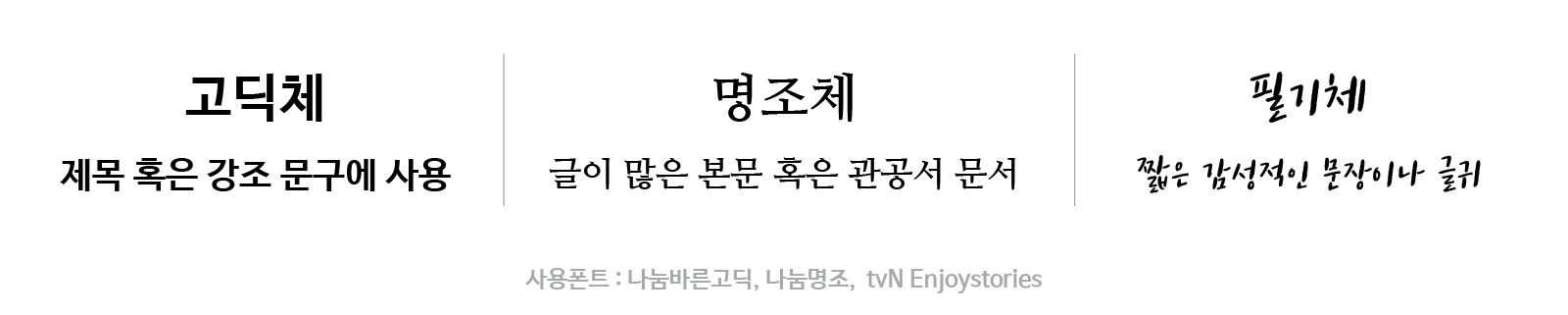
고딕체는 주로 제목이나 강조하고 싶은 단어나 문장에 사용합니다. 명조체는 주로 글의 내용이 많은 본문이나 관공서의 문서에 사용합니다. 필기체는 감성적인 광고지나 짧은 글에 자주 사용합니다. 이처럼 한글 폰트는 글자의 모양과 그에 따른 사용 목적이 분명하며 이것을 잘 지켜서 디자인을 하였을 때 보기 편하고 잘 정리된 느낌을 전달합니다. 이것을 우리는 가독성이 좋은 디자인이라고 말합니다. 가독성이 좋은 한글 폰트 디자인을 하기 위해서 실무에서 자주 사용하는 몇 가지 규칙을 소개해 드리겠습니다. 이 폰트 규칙은 고딕체와 명조체를 사용할 때 주로 사용되며 글자의 장평, 자간, 행간을 조정합니다. 장평은 글자의 폭을 의미합니다. 자간은 글자와 글자의 간격을 의미합니다. 행간은 글줄과 글줄 사이의 간격을 의미합니다. 아래 예시에 보이는 것처럼 고딕체와 명조체에 장평, 자간, 행간을 조정하였을 때와 하지 않았을 때의 가독성 차이는 큽니다.
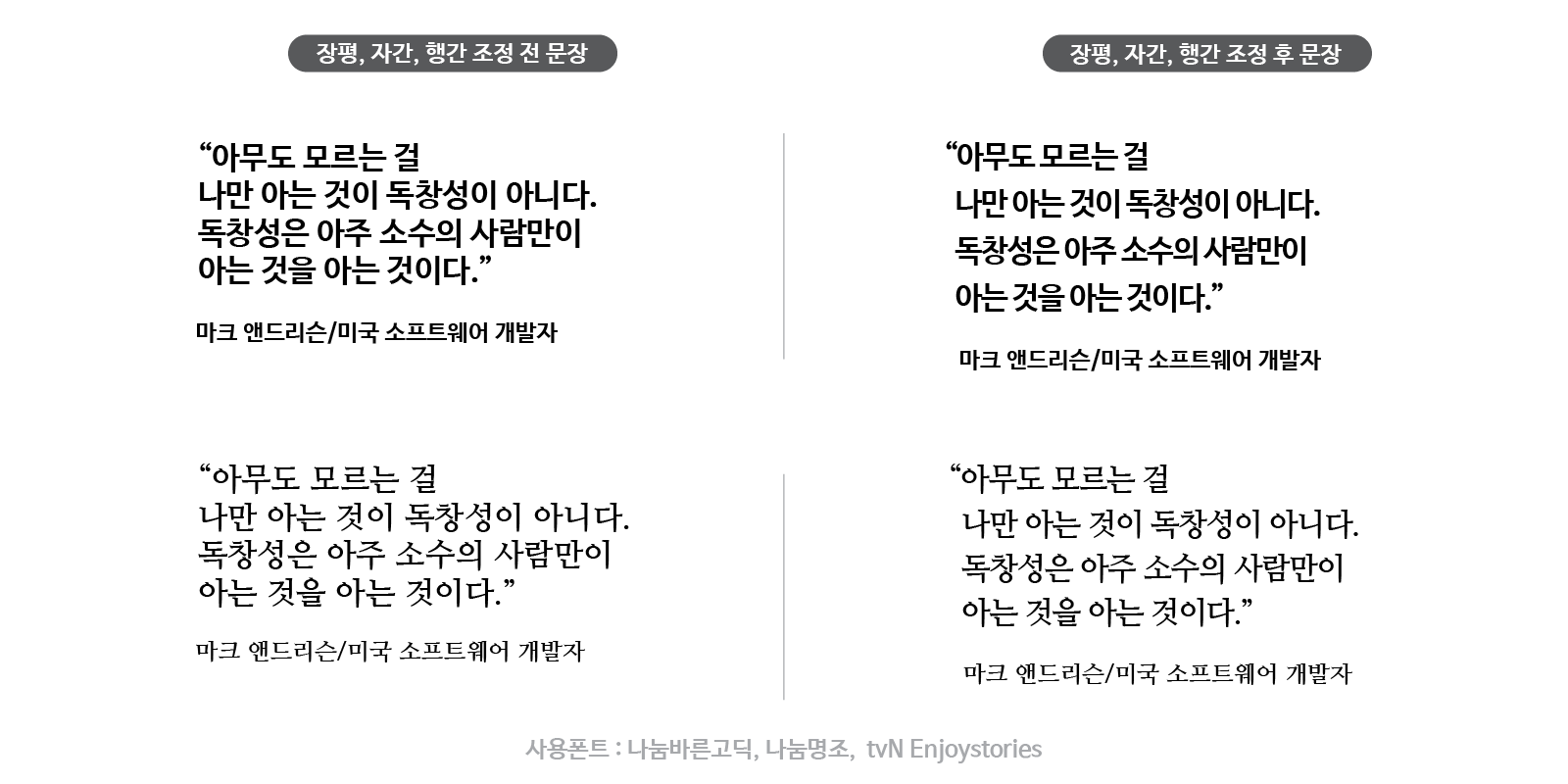
예시의 왼쪽과 오른쪽에 어떤 폰트 규칙이 적용되었는지는 다음과 같습니다.
조정 전 문장의 폰트 규칙
고딕체의 폰트
폰트 크기 : 24 / 장평 : 100 / 자간 : 0 / 행간 : 28.8
명조체의 폰트
폰트 크기 : 24 / 장평 : 100 / 자간 : 0 / 행간 : 28.8
조정 후 문장의 폰트 규칙
고딕체의 폰트
폰트 크기 : 24 / 장평 : 98 / 자간 : -50 / 행간 : 36
명조체의 폰트
폰트 크기 : 24 / 장평 : 98 / 자간 : -50 / 행간 : 34
우리가 한글 폰트를 사용하여 디자인을 할 때 폰트들이 뭔가 따로 노는 느낌이 들거나 안정감이 없는 느낌이 드는 이유는 바로 위의 세 가지 장평, 자간, 행간들에 가독성을 위한 조정이 안되어 있기 때문입니다. 폰트를 해체해서 디자인만을 강조하는 포스터 이외의 모든 글자들은 무조건 잘 읽혀야 합니다. 위의 대표적인 한글 폰트에 세 가지 폰트 규칙만 잘 적용하면 충분히 가독성 높은 좋은 한글 디자인을 할 수 있습니다. 아래한글, 워드, 파워포인트, 인디자인 등의 문서 편집 프로그램에서도 장평, 자간, 행간을 조정할 수 있으며 이 부분은 다음번에 포스팅하도록 하겠습니다.
사용방법